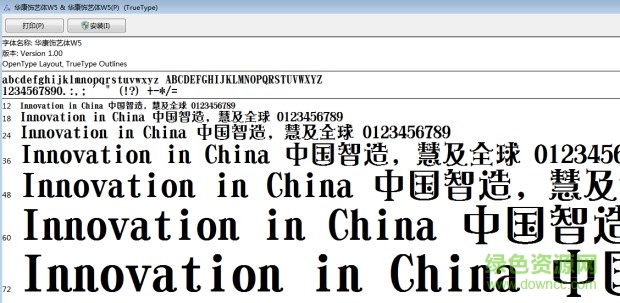
華康飾藝體簡(jiǎn)體w5
華康飾藝體簡(jiǎn)體下載盡在綠色資源網(wǎng)哦,華康飾藝體簡(jiǎn)體字形粗大筆墨較重,非常適合做標(biāo)題使用,有興趣的朋友趕緊來(lái)綠色資源網(wǎng)下載吧!
華康飾藝體簡(jiǎn)體介紹
華康飾藝體W5是一款專(zhuān)門(mén)為廣告設(shè)計(jì)而打造的精美字體。當(dāng)然也有部分設(shè)計(jì)文件也會(huì)用到該字體。需要的廣告設(shè)計(jì)朋友們快來(lái)綠色資源網(wǎng)下載吧!